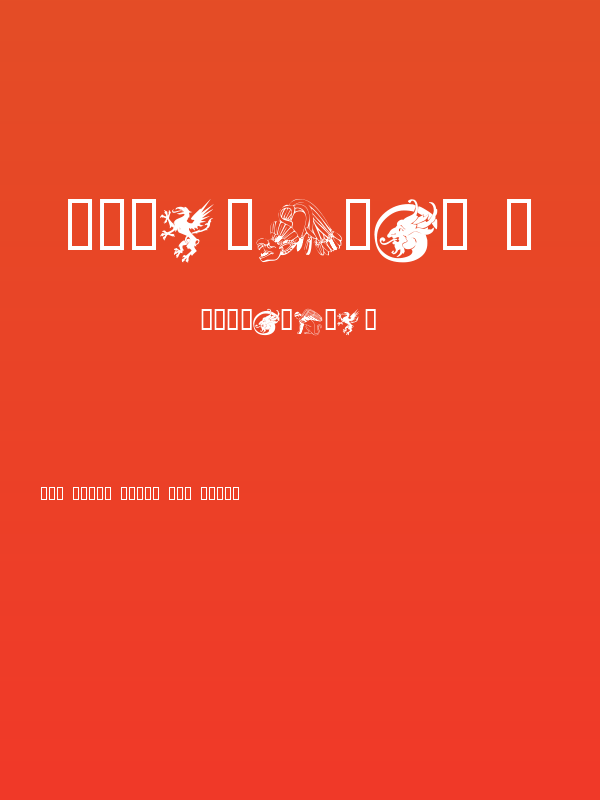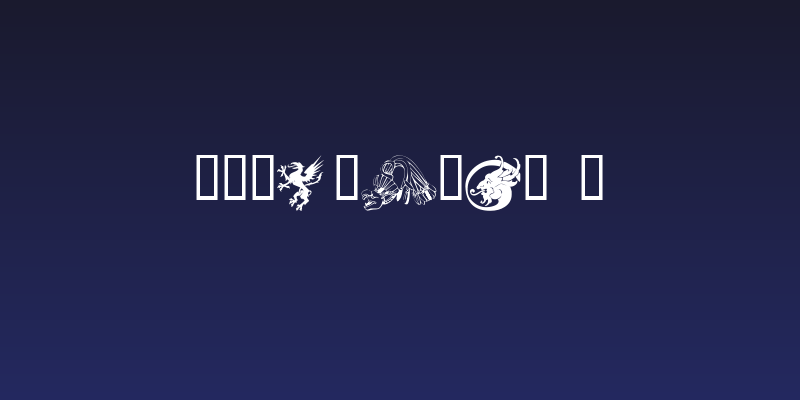
Mythology 1 Font
✎ Dingbats
| Anwendungsfall | Decorative art, Fantasy themes |
| Vorgeschlagene Projekte | Ideal for fantasy-themed projects, book covers, game designs, or decorative art pieces. |